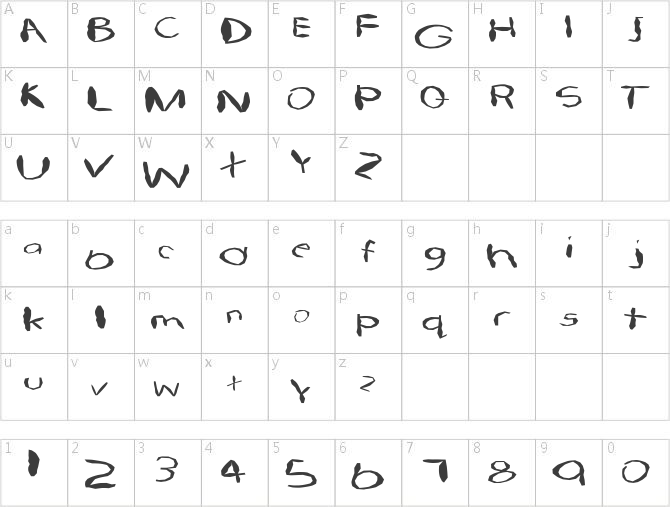
FZ HAND 22 MANGLED EX 詳情頁(yè)
FZ HAND 22 MANGLED EX字體字庫(kù)是一款讓人賞心悅目、百看不厭的英文字體,適合各類廣告和產(chǎn)品包裝設(shè)計(jì)應(yīng)用,字體大小0.05MB,格式為ttf字體,上傳用戶是小籃子,作者/版權(quán)方為未知